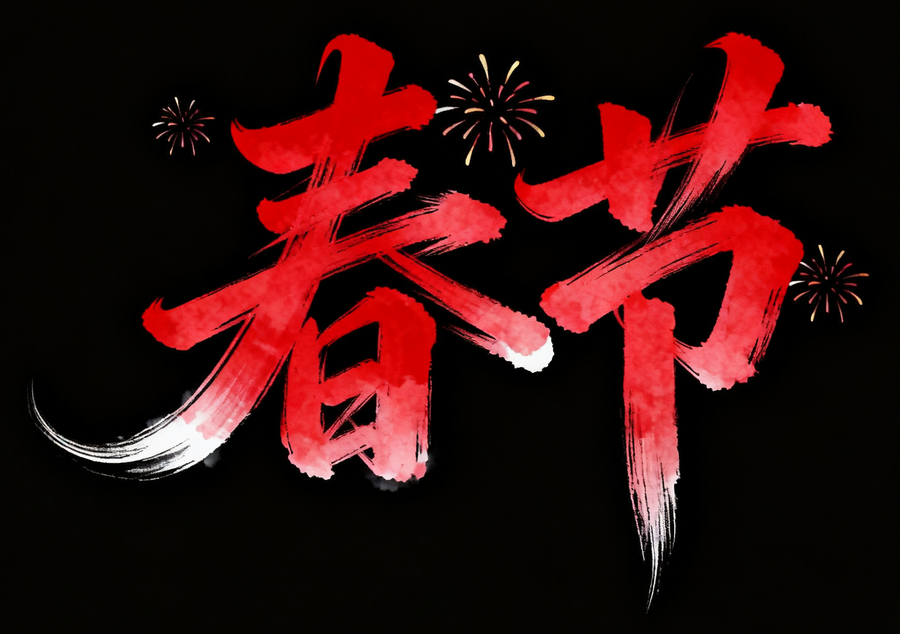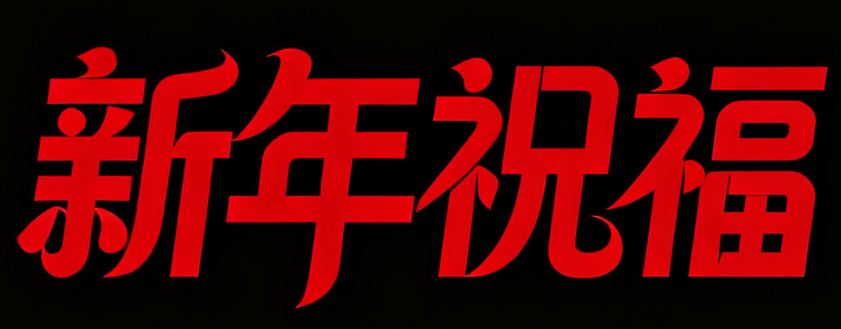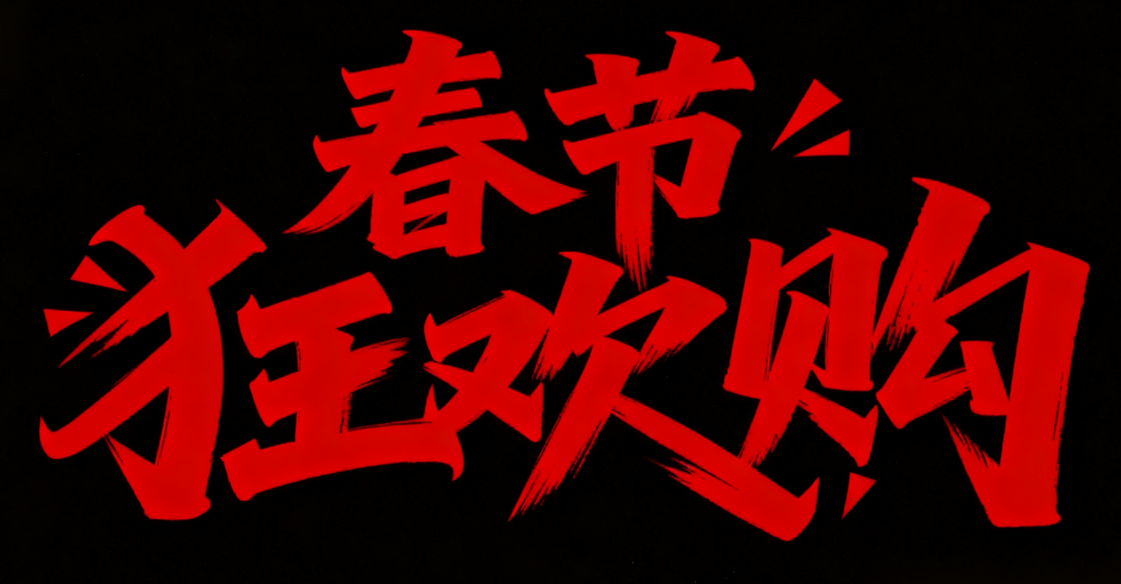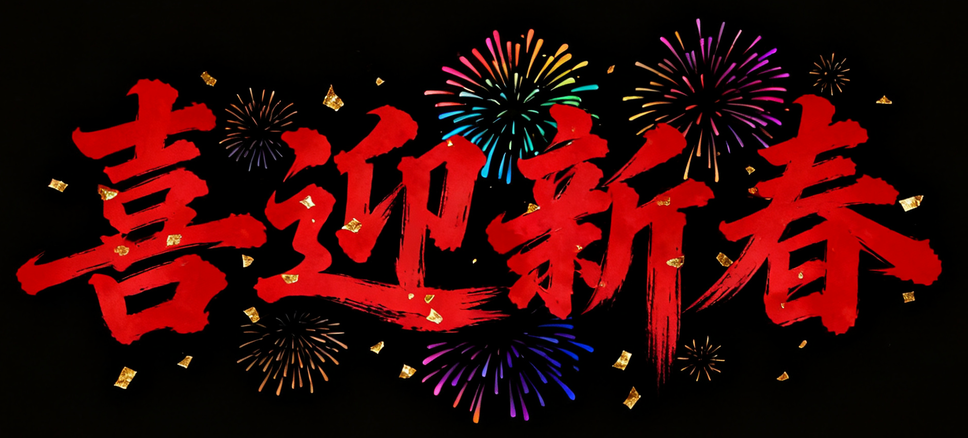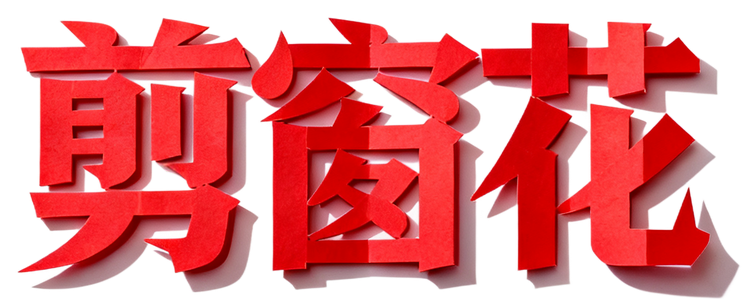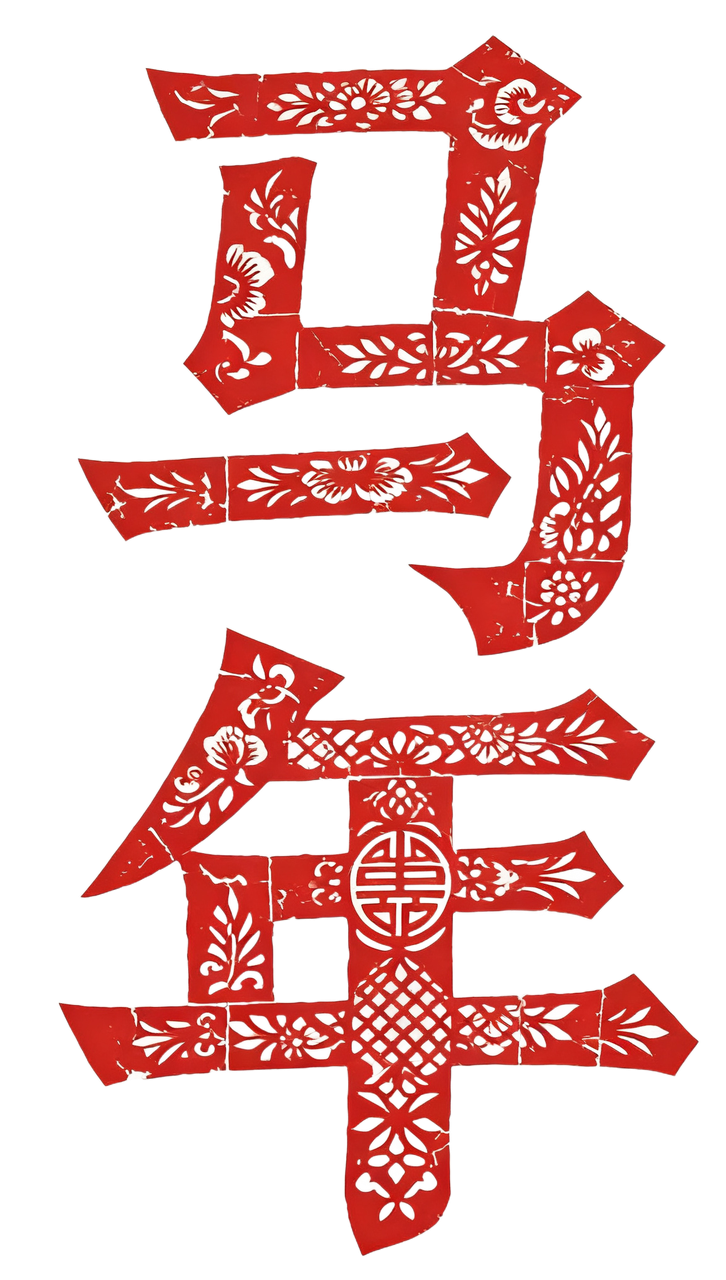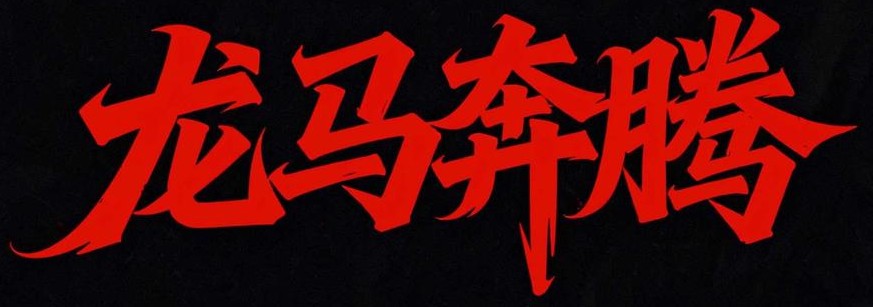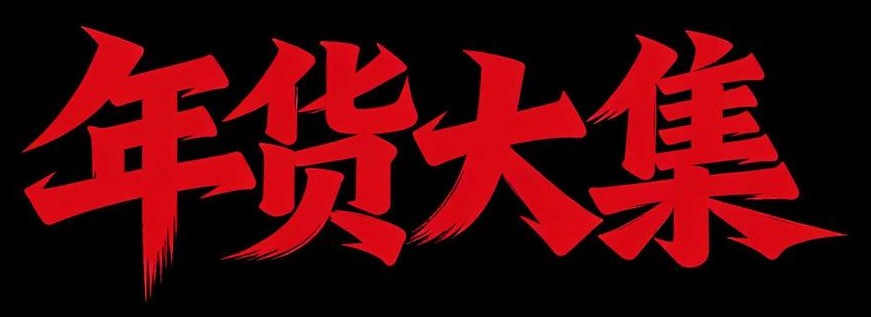
春节设计,如何能少的了富有中国风设计与国潮设计韵味的标题字体?本文整理了9款字由AI字体里的年味儿字体设计素材,只需输入文案,即可一键生成专业级节日设计素材。
纯正的中国风设计书法字体,笔触流畅,飞白自然,简洁大气。搭配的小型烟花点缀,简约而精准地烘托出带有传统文化味道的“爆竹声中一岁除”的意境。适用于各类海报标题、壁纸设计。
现代感的字体设计,笔画末端带有喜庆的卷曲装饰,精致而不失温馨,非常适合作为春节朋友圈海报、社交媒体祝福长图的标题。字体设计的亲切感能促进用户转发与传播。
秀丽笔画风格的毛笔字体富有张力与动感,布局充满节奏感,完美融合传统年味与现代促销气息,是电商促销字体、直播间背景素材、标题设计素材的绝佳选择。可直接用于网店设计素材,如店铺首页大图、活动 banner、商品详情页促销标签,营造“节日+抢购”的热烈氛围。
洒脱漂亮的大楷楷书书法字周围,环绕五彩烟花与金色碎屑,营造出普天同庆、热闹欢腾的视觉效果,场景感极强。非常百搭的节日设计素材。无论是线下商场海报标题字体、线上活动首页,还是作为视频特效字体、SVG动态字体海报核心元素,都能迅速拉升节日的欢庆格调。
带有折纸立体感的特效字体,充满手工艺的温度,适合用于具有互动性的春节朋友圈海报或H5活动页面互动卡片设计素材,用于抽奖、答题环节,主题鲜明,趣味性强。
将窗花剪纸特效字体与花卉等传统吉祥图案深度结合,专为春节设计,天生带有非遗文化的属性。可直接用作年度限定版的低成本logo字体设计,用于礼品设计、文创设计,赋予产品传承的意味
字体边缘干净,笔触豪放不羁,富有刚劲的力量,充满豪迈积极的精神。这套字体设计模板非常具有视觉冲击力,适合作为企业年会主视觉模板的核心标题,寓意企业精神昂扬向上。也适用于汽车品牌、金融品牌、地产品牌等在春节期间的硬朗风格海报标题字体。
厚重饱满的书法字体,犹如市集招牌,直接唤起人们对传统年货采办的热闹记忆,促销号召力直接而质朴。适合用在电商“年货节”活动海报的促销标题素材或线下商场促销设计的主视觉。
从传统书法字体到现代国风手书字体,剪纸窗花特效字体到C4D立体质感字体,无论是文创设计、国潮设计、温情祝福、吸睛促销还是震撼KV主视觉,字由AI字体将满足你的多元营销诉求和设计需求。百款不同风格的春节字体设计素材、海报标题模板,输入文字即可生成同款,无需PS功底和AI训练咒语,再也不怕设计没年味儿!